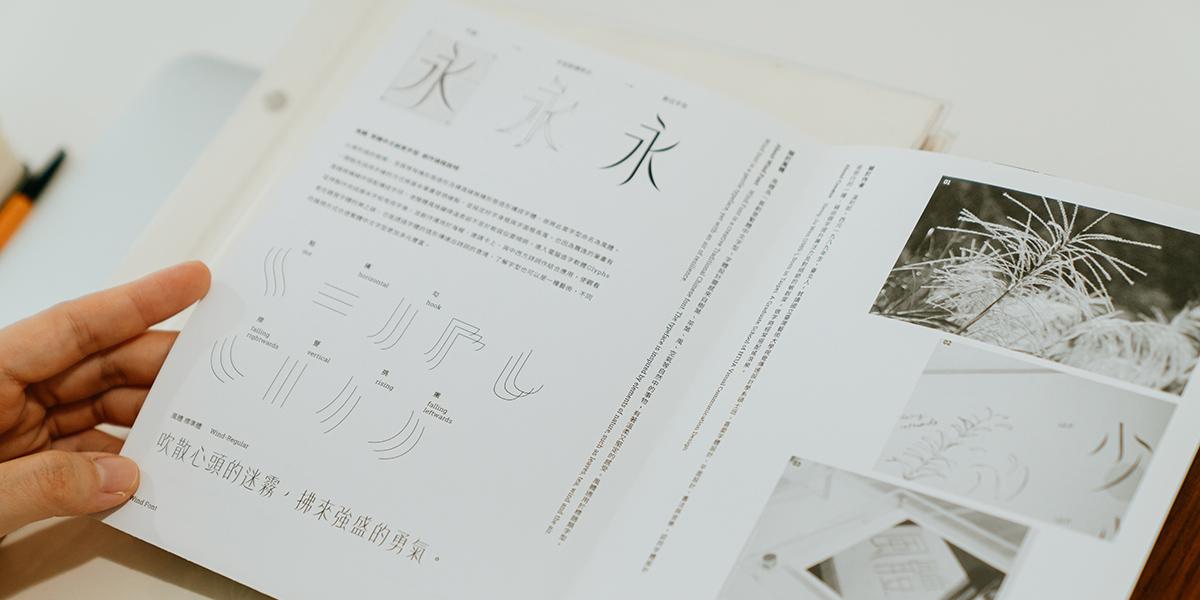
本サイトの読者の中には「フォントが好き!」という方も多いのでは?けれども海外のフォントについては、あまり知るチャンスがありませんよね……。そこで、ユニークな試みで新たなフォントを誕生させる「台湾」をフィーチャー。台湾の今のフォント事情を深掘りました。台湾在住のライター・近藤弥生子さんによる取材は、フォントマニア必見です!※文中の為替レートは、1ニュー台湾ドル=4円で換算しています
はじめに
インターネットの普及や訪日インバウンドの発達などにより、商品パッケージや書籍・パンフレット、Webサイトなどにおける多言語展開は、今や珍しいことではなくなってきました。なかでも英語に次いで頻繁に登場するようになったのが「中国語」。中国語の漢字は大きく分けて2種類があり、そのうち主に台湾と香港で使われている漢字を「繁体字」といいます。中国大陸では簡略化された「簡体字」が使われているのに対し、画数が多く複雑な字体で、「正體」とも呼ばれています。
そんな「繁体字中国語」の字数は13,000〜15,000字といわれ、フォントに収録される字数は少なくても7,000字程度。人名や、使われる字が異なる香港エリアまでカバーしようとすると10,000字を軽く超えてしまうほど。欧文フォントの収録字数が1,000字程度、日本語フォントが9,000字強であることを鑑みても、その複雑さが際立ちます。さらに、違法ダウンロードが蔓延している台湾では「フォントを買う」という概念が定着していなかったため、わざわざ難易度の高い繁体字フォントを作って売ろうという会社が出てきにくかったという事情があります。
ところが近年ではクラウドファンディングで資金を調達し、次々に個性ある「繁体字フォント」が登場するなど変化が起きています。そこで今回は台湾のフォント業界を牽引する3つのフォント会社へ、日本のメディアとして初となる取材を敢行してきました。中国語フォントをお探しの方は必見です!
玉川設計所 風に揺らぐ涼しげな「風体 Wind Font」
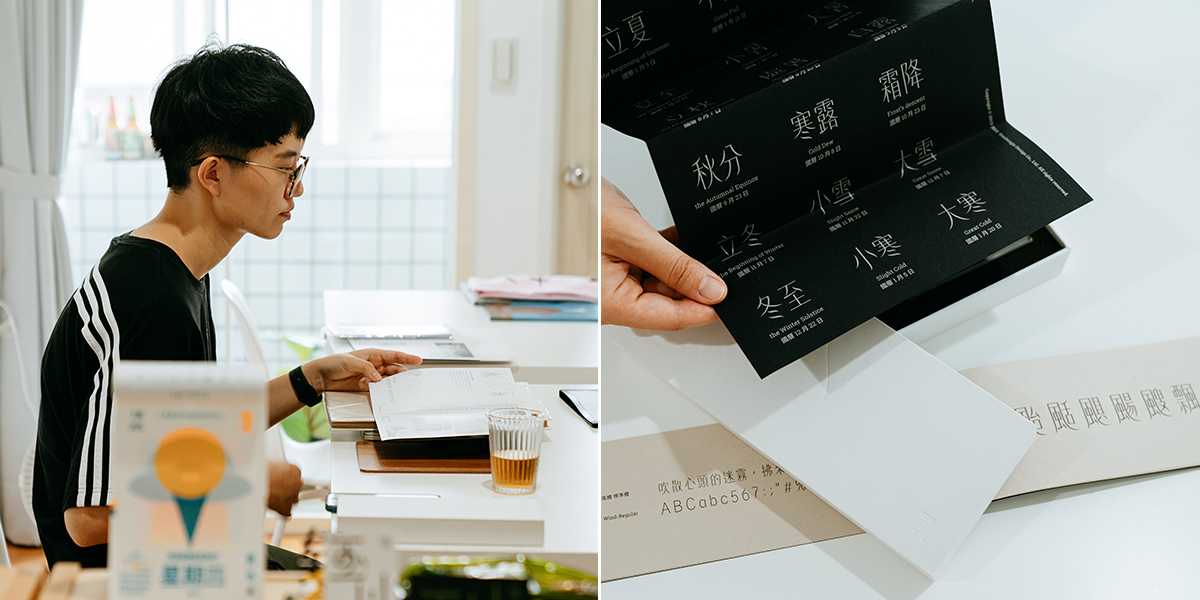
まず最初にご紹介するのが、台湾人デザイナーのWenさん(溫珩如さん)がクラウドファンディングを利用して生み出した「風体 Wind Font」。南国台湾の優しい風に揺らぎ漂っているような美しい書体が特徴のフォントだ。
Wenさんが「風体」を作ったのは、2015年に行われた大学院の卒業制作の課題がきっかけだった。教師から出された「空気」というテーマから、風に吹かれる木の葉や茶葉などをイメージした字体として8つの字をデザイン。卒業展は盛況となり、確かな手応えを感じたという。
小学1年から大学まで書道を続けていたというWenさんは、字の筆法に並々ならぬこだわりを持つ。揺らぎという個性を持った「風体」が、見出しだけでなく本文にも使えるほど均一性が取れているのは、そんな彼女だからこそ成し得たのだと思わせる。
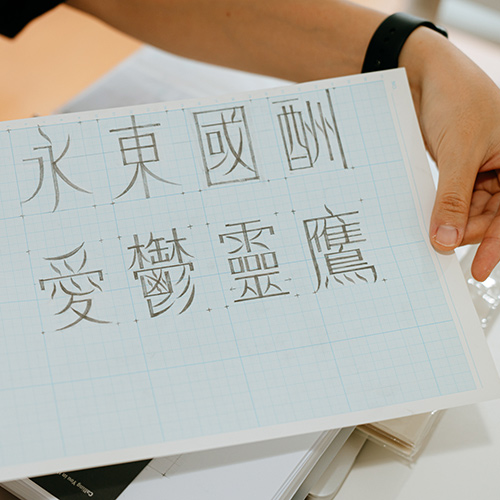
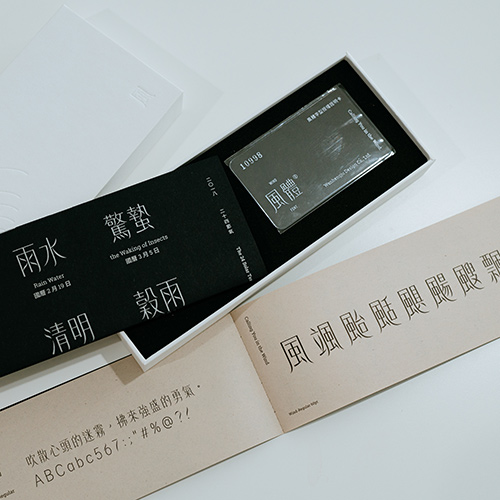
大学院でデザインを専攻した彼女は、在学中から台湾のフォントメーカー「justfont」でインターンとして働き、経験を積んだ。そして、卒業後の2017年には自ら「風体」の発売を目指して、クラウドファンディング上でプロジェクトを始動。3カ月足らずの間に654名の支持者から、目標の100万ニュー台湾ドルを大きく上回る約185万ニュー台湾ドル(日本円で約740万円)を調達した。
そこで得た資金を元に、デザイン事務所「玉川設計所」を設立。2018年には「風体」を無事に完成させ、市場に出した。フォントデザインの傍らで、マーケティングや講演会への出演などすべてを1人でこなしている。台湾ではこれまでほとんど見ることのできなかった、ニュータイプのフォントデザイナーだ。
こうしたフォントデザイナーの台頭は、台湾のデザイン界にとってはひとつの大きな変化だといえる。なぜならこれまでの台湾では「お金を払ってフォントを買う」という概念が全くといっていいほど定着しておらず、知名なデザイナーでさえ違法ダウンロード版を使用しているような状況が蔓延していた。フォントメーカーはおろか、フォントデザイナーが独立してやっていけるような市場ではなかったからだ。
そして「風体」は、台湾のデザインアワードにて「2019 台灣金點設計獎」を受賞。2020年夏には、台湾の古い街並みでよく見かけられる隷書体をベースに、台湾のお寺の屋根によく見られる「燕尾脊」という尖ったモチーフを取り入れて作られた「拳体」をリリース予定だ。取材時には、この新しいフォントのために「事前インターネット調査」を行っている真っ最中だった。
ちなみに、この「事前インターネット調査」も、実に台湾らしいフレキシブルさが現れた取り組みと言える。日本ではフォントに限らず新製品をリリースするまで、その内容は非公開とされることが多いと思う。ところがここ台湾では製造業の多い関係か、「50〜60%まで完成したところでいったん市場の反応を見る」ということが業界問わず良いこととして行われているのだ。
Wenさんの事前調査は主にマーケティング目的で行われており、アンケート協力者に向けて「この『拳体』をどんな用途に使いたいと思っていますか?(複数回答)」と呼びかけ、自分が用意したいくつかの選択肢に投票してもらう。こうした事前調査は新しいフォントをリリースすることの告知にもなり、さらに購入希望者にはより「参加している感」を味わってもらうことができる。
「調査をしていると、クラウドファウンディングでは見えなかったことが見えてきます。実はたくさんの非デザイナーや、デザインを勉強している学生たちがフォントを買ってくれていることも分かりました。だからフォントの販売を開始するときには、より購入者が想像できるように模範イメージを作ることが必要です。まだ進歩できるところがたくさんありますね。日本のデザインにたくさん影響を受けているので、いつかは日本語の平仮名・カタカナにも挑戦したいです」とWenさんは語ってくれた。
風体 Wind Font
10,000字以上の繁体字中国語、香港で使われている字体等を収録
モリサワ 多言語化に対応する「UD書体」を販売
2024年に創業100年を迎える日本を代表するフォントメーカー「モリサワ」は、2014年7月に海外初の拠点として台湾・韓国・アメリカにそれぞれ100%出資の子会社を設立、販売拠点として運営している。ほぼ全書体の日本語フォントをデスクトップフォント・Webフォント・ゲームなどのソフトウェアへの組込フォントとして販売していたが、そこに2019年からは繁体字中国語フォントが加わっている。
モリサワ台湾を立ち上げから統括する董事長(台湾の取締役から選定され、法人を代表する責任者のこと)の山村進仁さんが、その経緯を教えてくれた。「これまで台湾で6年の間、日本のフォントを台湾・中国大陸向けに販売しているうちに、台湾のデザイナーたちから高品質な繁体字中国語フォントの強いニーズがあることが分かったので、2019年5月にユニバーサルデザイン(UD)対応の繁体字中国語「UD新ゴ」4書体を、そして2020年6月末に繁体字中国語「UD黎ミン」6書体をリリースしたばかりです。また、多言語対応ができるよう、簡体字中国語、ハングルも取り揃えています」。
台湾でユニバーサルデザイン(UD)対応のフォントは、モリサワが手掛けたものが初めてとなる。「UDは台湾でまだまだここ数年で認識されるようになったばかりですが、パイオニアとしてその概念を広めていきたい」と山村さん。
モリサワは、2011年から台湾のフォントメーカー「アーフィック(ARPHIC、文鼎)」とフォント事業で資本提携しており、日本および台湾でアーフィック社製フォントの代理販売を行っている。UD対応の中国語(繁体字・簡体字)フォントを携え、今後は台湾でより一層の啓蒙活動やデザイナーとの交流に力を入れていくというモリサワ台湾。台湾におけるフォント文化の黎明期に、フォント界の重鎮として存在感を発揮していくだろう。
繁体字中国語「UD新ゴ」/繁体字中国語「UD黎ミン」
justfont 台湾を代表するフォント「金萱」
最後にご紹介するのは、台湾のフォントシーンを牽引するフォントメーカー「justfont」。2015年に「フォントを買う概念がなかった多くの台湾人が、人生で初めて買ったフォント」と呼ばれる「金萱」を世に送り出し話題となったメーカーだ。クラウドファンディングを通じてフォントを作ったのも彼らが初めてだった。1カ月間におよそ2,593万ニュー台湾ドル(日本円で約1億372万円)を調達した記録は、いまだ破られていない。
そんな同社でフォントデザイナーを務めるRongさん(曾國榕さん)、Boldさん(簡國庭さん)が取材に応えてくれた。「私たちの会社でデザインしたフォントには、最も完成度の高い『金萱』と、そこからスピンオフした『金萱那提』、オープンソースの無料フォント『粉圓』があります。また、台湾がもっと多種多様な中国語フォントを生み出せるよう教育にも力を入れており、フォントデザイナーの養成も行っています。
「台湾を代表する繁体字中国語フォントを作ろう」という触れ込みで作られた「金萱」ができるまでのストーリーには、なんと日本が関係していた。
「私たちは、友人の柯志杰さん(butさん)が2013年に作ったFacebookグループ『字嗨』に、管理人として参加しています。現時点で参加者は8万5,000人にのぼり、字やフォントが好きな人たちはみんなここに集まっています。このグループでは、街や道端で見かけた素敵なフォントの写真が投稿し、何のフォントが使われているのかを答える……という遊びで盛り上がっています。そして私たちはある発見をしました。そこで投稿されるフォントの多くが、モリサワの『フォーク』と『丸フォーク』だったのです。明朝体とゴシック体を混ぜたようなスタイルのフォントは、当時の台湾にはなかったけれど、明らかに台湾人に好まれているのフォントだということが分かりました。そこで私たちは、『無いなら自分たちで作ろう』と考えたのです」とRongさん。
「justfont」では、フォント関連のブログを継続していたため、多くの知識・コンテンツを蓄積していた。そのため、「金萱」が作られる前から、すでに顧客になるであろう人たちを十分に引きつけていたのだ。これこそが「金萱」成功の最大の理由と言えるだろう。
また、冒頭で紹介した「風体」のデザイナーであるWenさんも「justfont」でインターンをして経験を積んでいるが、ここから羽ばたいていったフォントデザイナーはそれだけではない。「justfont」では、これまで4年以上、毎月無料のフォント関連講座を主催し、これまでに4000人以上が受講しているという。そのほかにも大学や企業で講義もしているため、その影響力は計り知れないものがある。
このように、台湾のフォントデザインは今とてもおもしろい時期に。では、彼らが次に目指しているのはどんなことなのでしょうか……。「justfont」のRongさんとBoldさん、そして「風体」のWenさんが口を揃えて言っていたのが「日本語のひらがなとカタカナにも挑戦したい」ということでした。
それは、実に台湾ならではの事情から……。「メイドインジャパン」が付加価値として非常に評価される台湾において、台湾企業は自らの製品パッケージなどに日本語を添えるだけで、販売価格を吊り上げても売れることを知っています。日本企業でなくても、日本企業を装ってたくさんの店舗や商品が開発され、中〜高価格で販売されるのです。そんな特殊なニーズから、デザイナーたちは例え繁体字フォントであっても、ひらがなとカタカナが欠かせません。
その代表格が日本語の「の」。英語の「‘s」といった意味で使われますが、これらが看板や商品名にかなり多く登場し、記号のように使われているのです(画像中央、右参照)。ほかにも「おいしい」などが挙げられますが、根っからの商売人である台湾人にとっては、費用対効果があればフォントも売れるということでしょう。